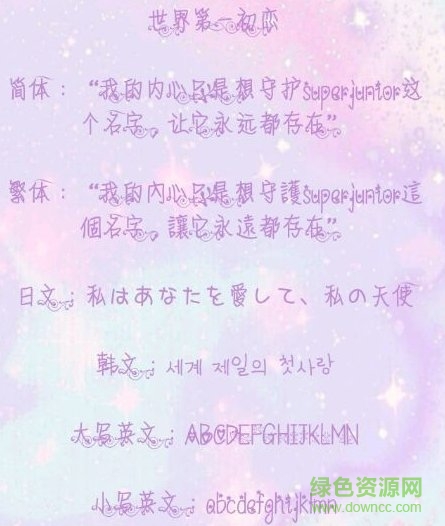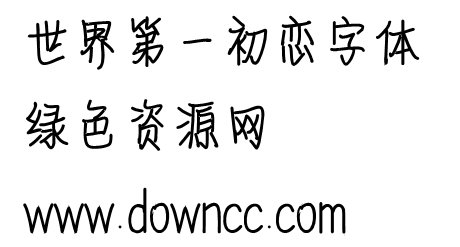
世界第一初戀字體ttf
世界第一初戀字體是一款蕩漾著青春活潑、熱鬧生動(dòng)氣息的可愛字體,讓你的文字更具活力,支持中文繁簡體、日韓語言等,喜歡的朋友快來綠色資源網(wǎng)體驗(yàn)吧!
世界第一初戀字體介紹
我的內(nèi)心只是想守護(hù)這個(gè)名字
讓它永遠(yuǎn)都存在
嵐情書體
世界第一初戀字體是網(wǎng)友嵐補(bǔ)充修改的情書字體,完善了字庫,給文字增加了更多的花型符號(hào)和裝飾,讓文字更加動(dòng)人起來!